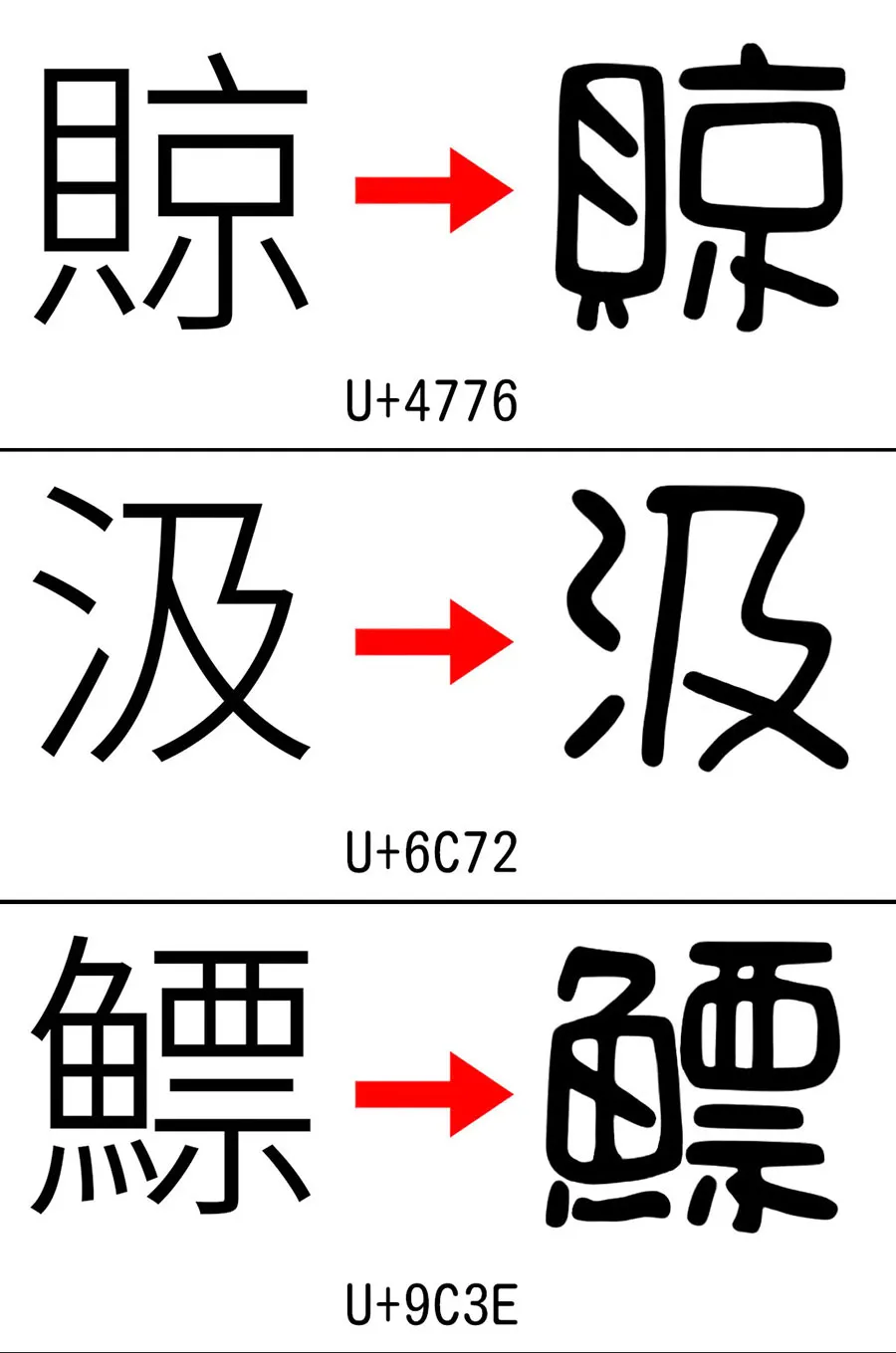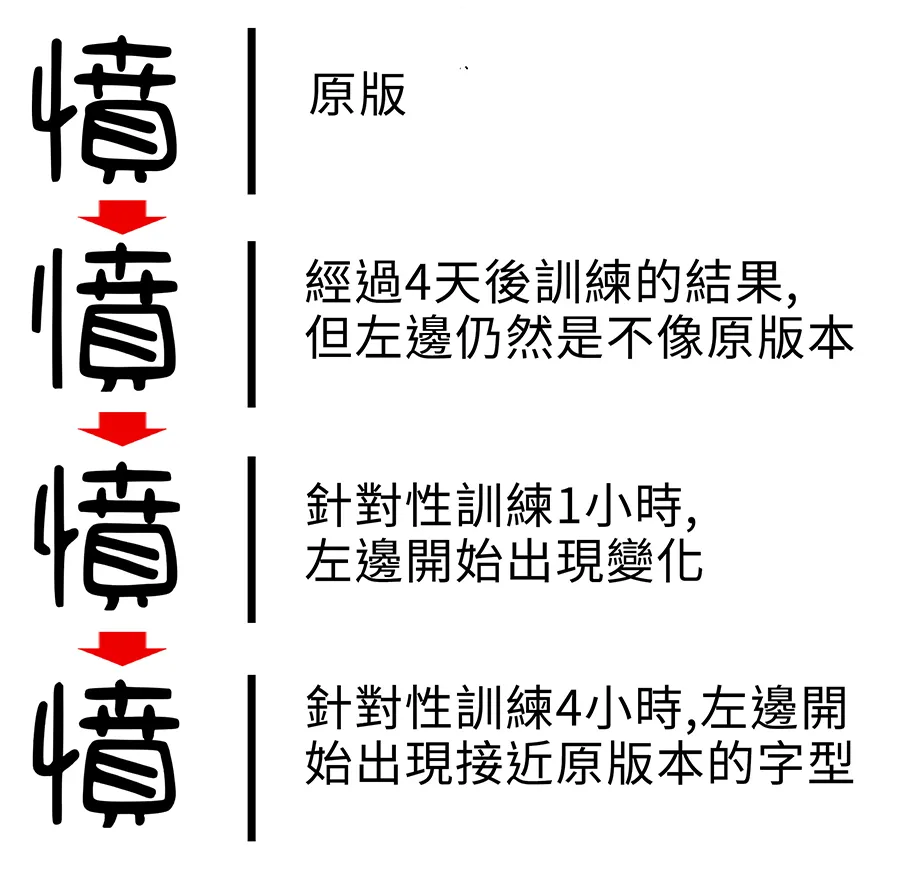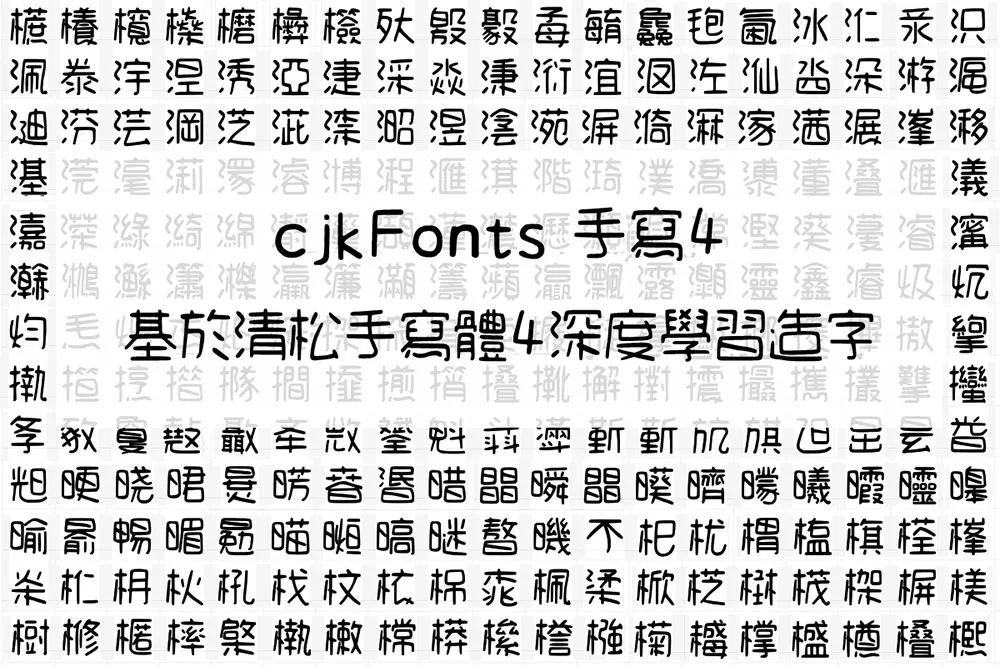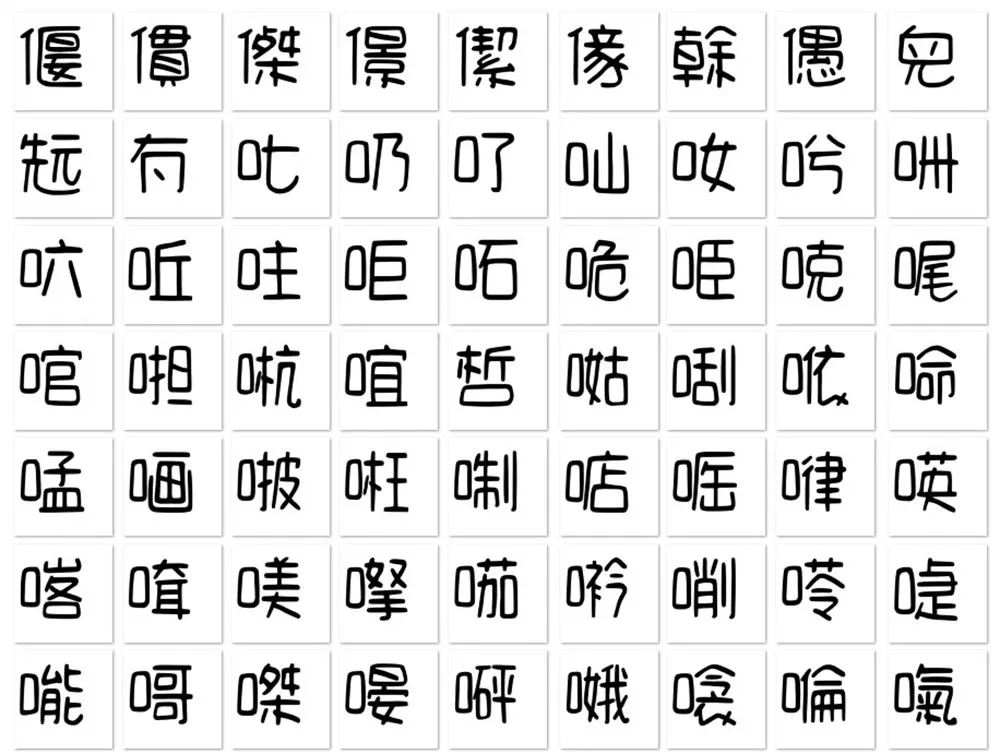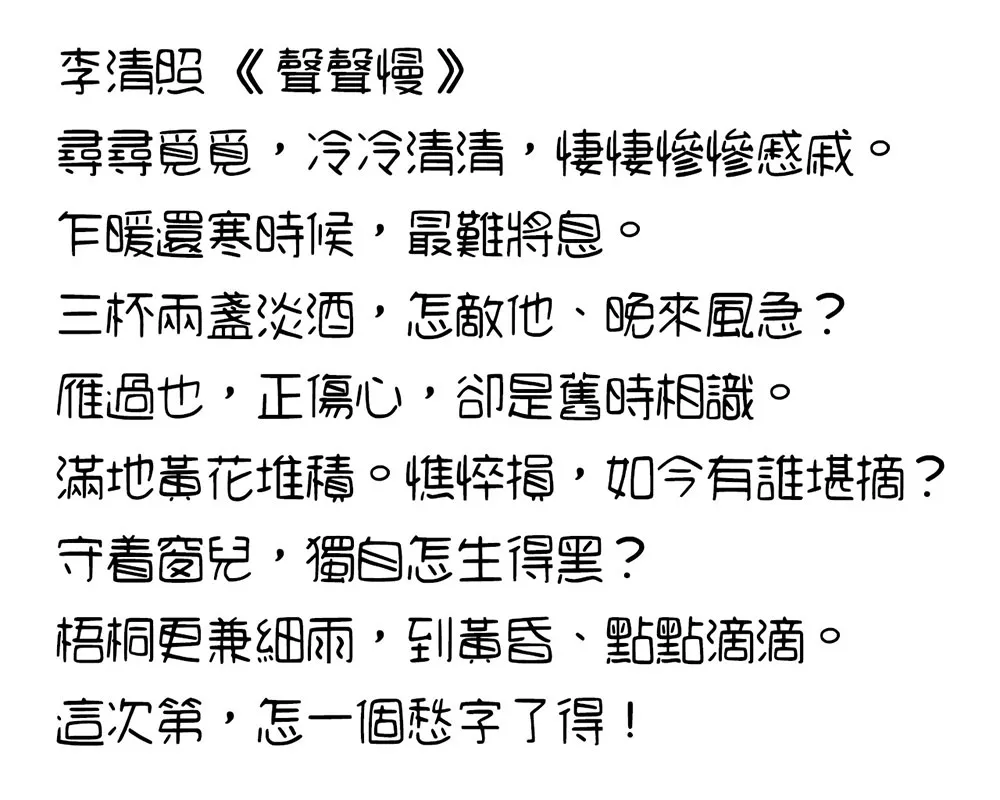
cjkFonts手寫4是基於清鬆手寫體4透過AI深度學習造字,原本清鬆手寫體4大約有4千幾百字,使用AI已造了2萬7千字,但因為要時間後期製作,現在只釋出大約1萬2千字,其餘的字待有時間才再加入。
由於是電腦學習了字體的特點及風格後,每個字根據學習後的數據造字,所以字體的風格會跟清鬆手寫體4有輕微的分別。
今次是1萬2千字的版本,大約用了2個月時間完成製作。清鬆手寫體4的風格跟一般字變化比較大,在整過訓練過程中,要反覆檢視結果,然後再訓練,再檢視,直至大部份的字體跟原版接近才能開始後期製作。